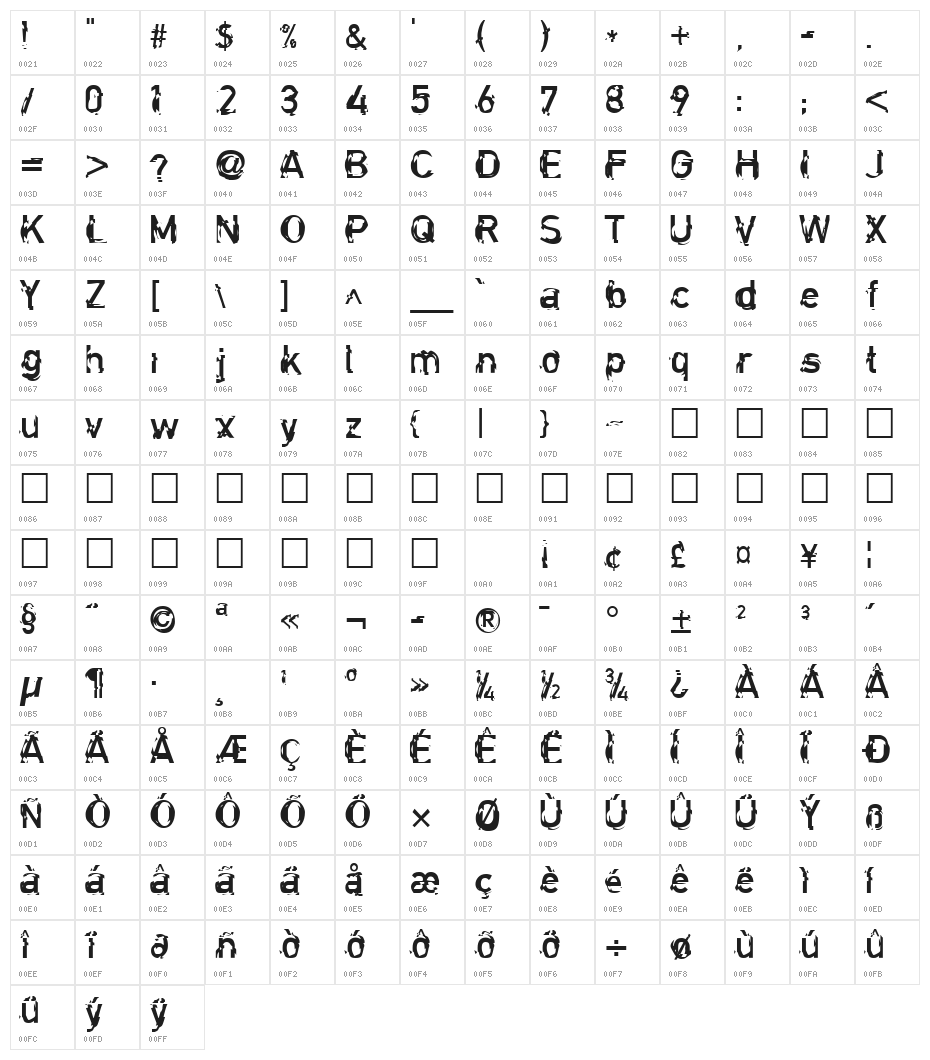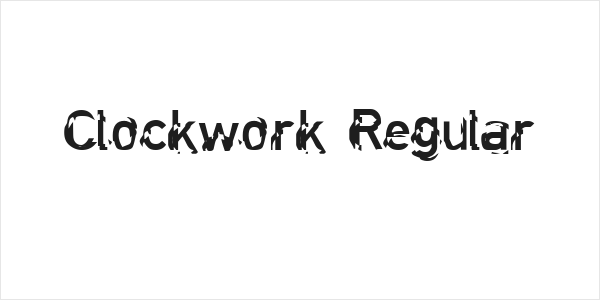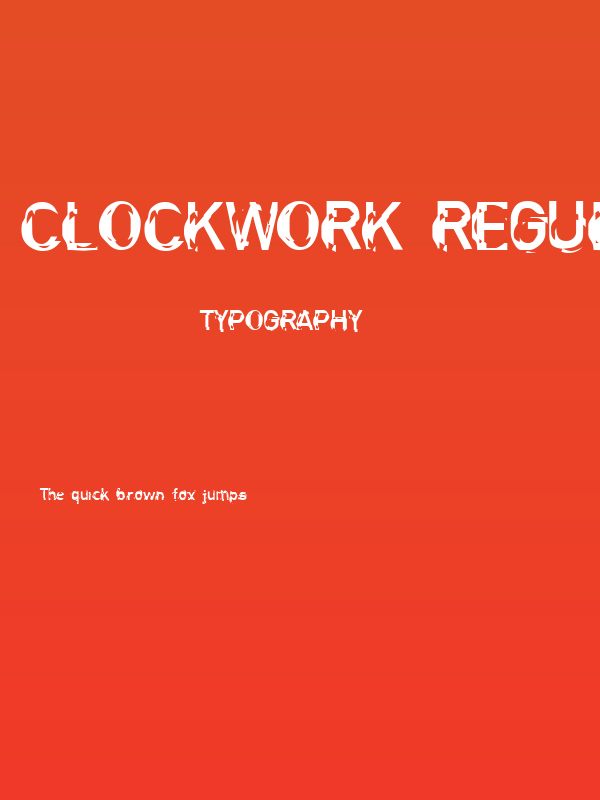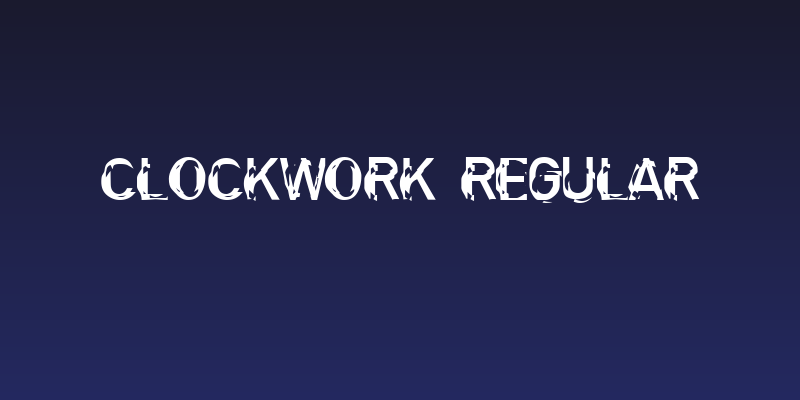
Clockwork Regular Font
| Stil general | Industrial, Mechanical, Distressed |
| Proiecte propuse | Ideal for posters, album covers, video game titles, and branding that requires a gritty, industrial look. |